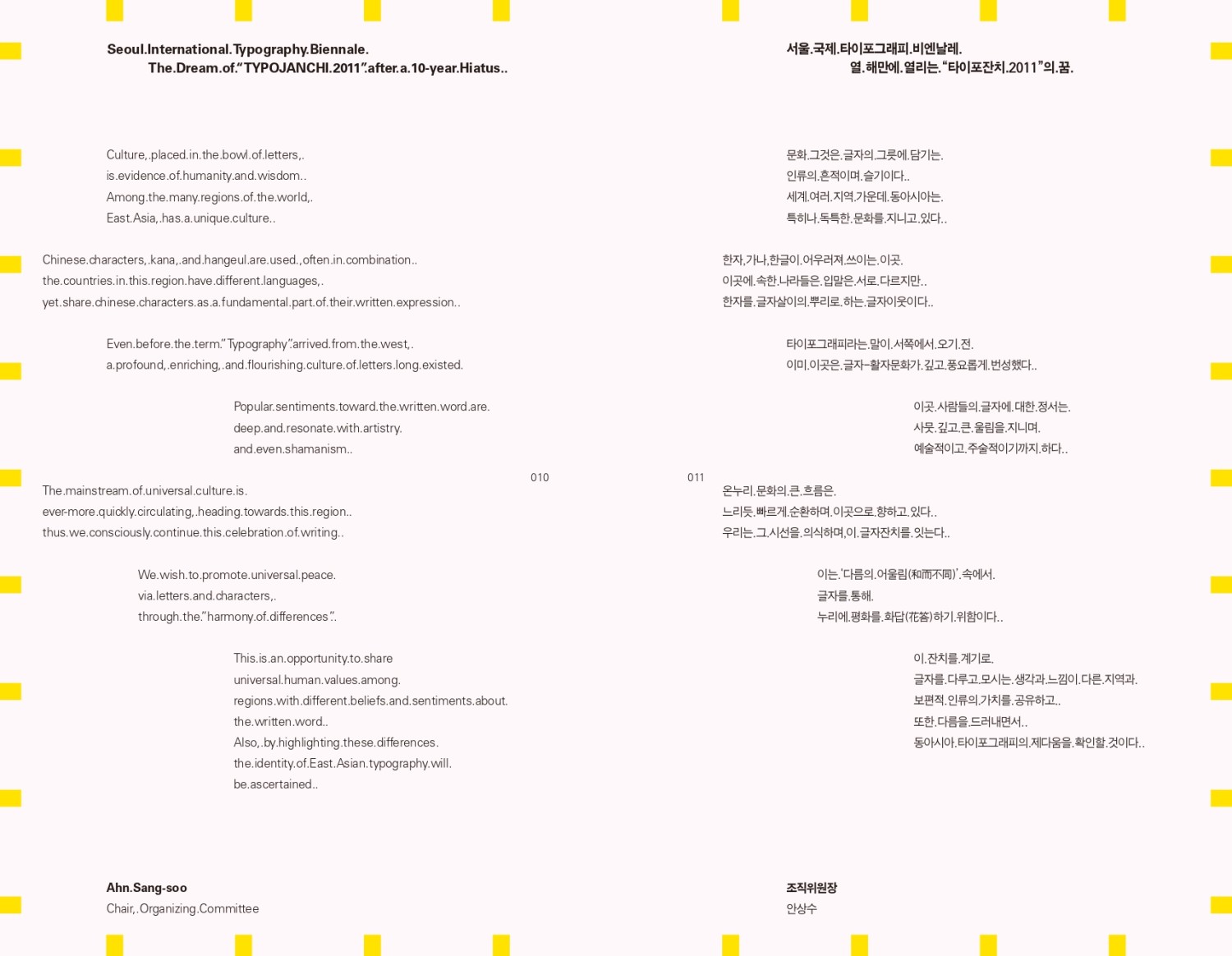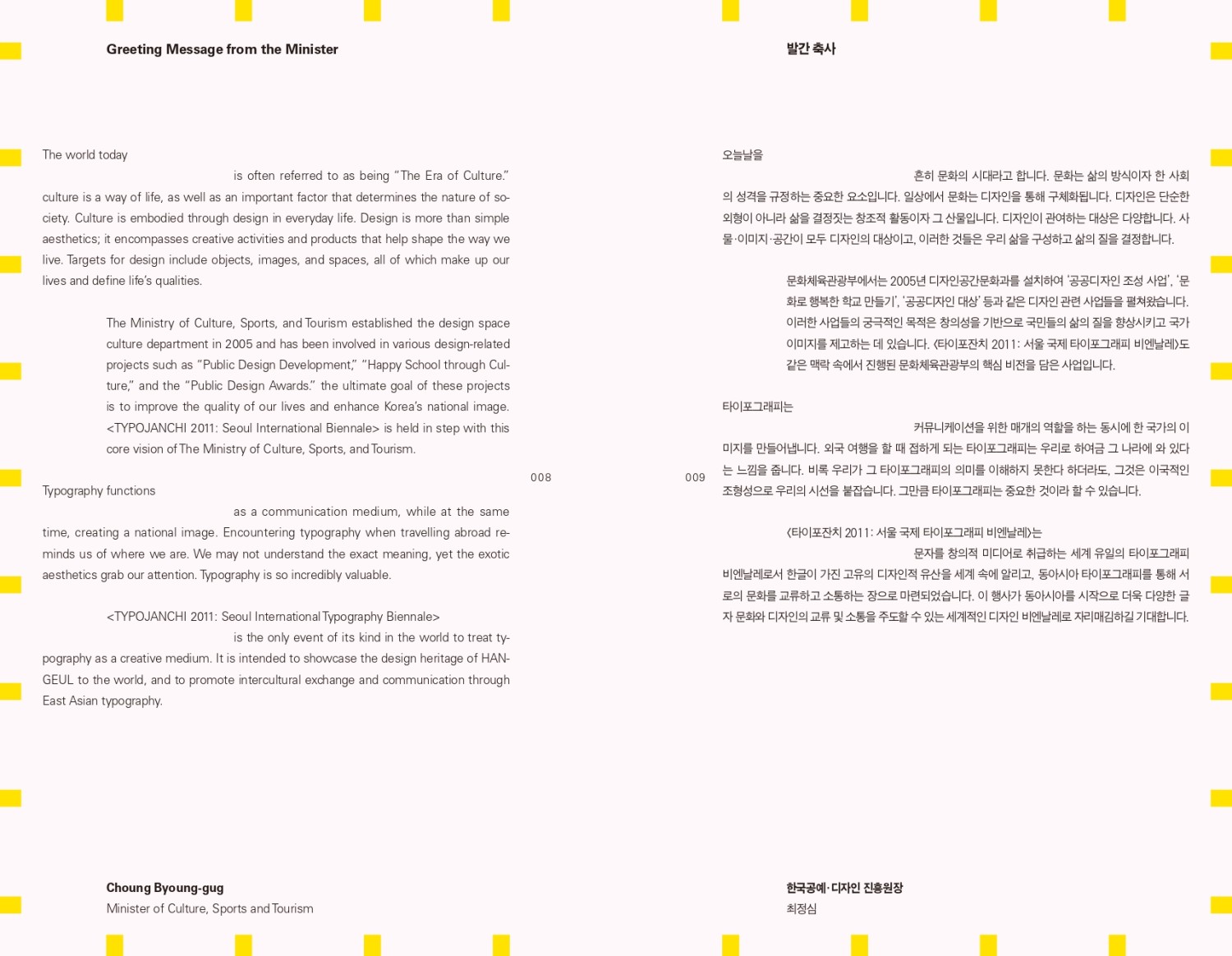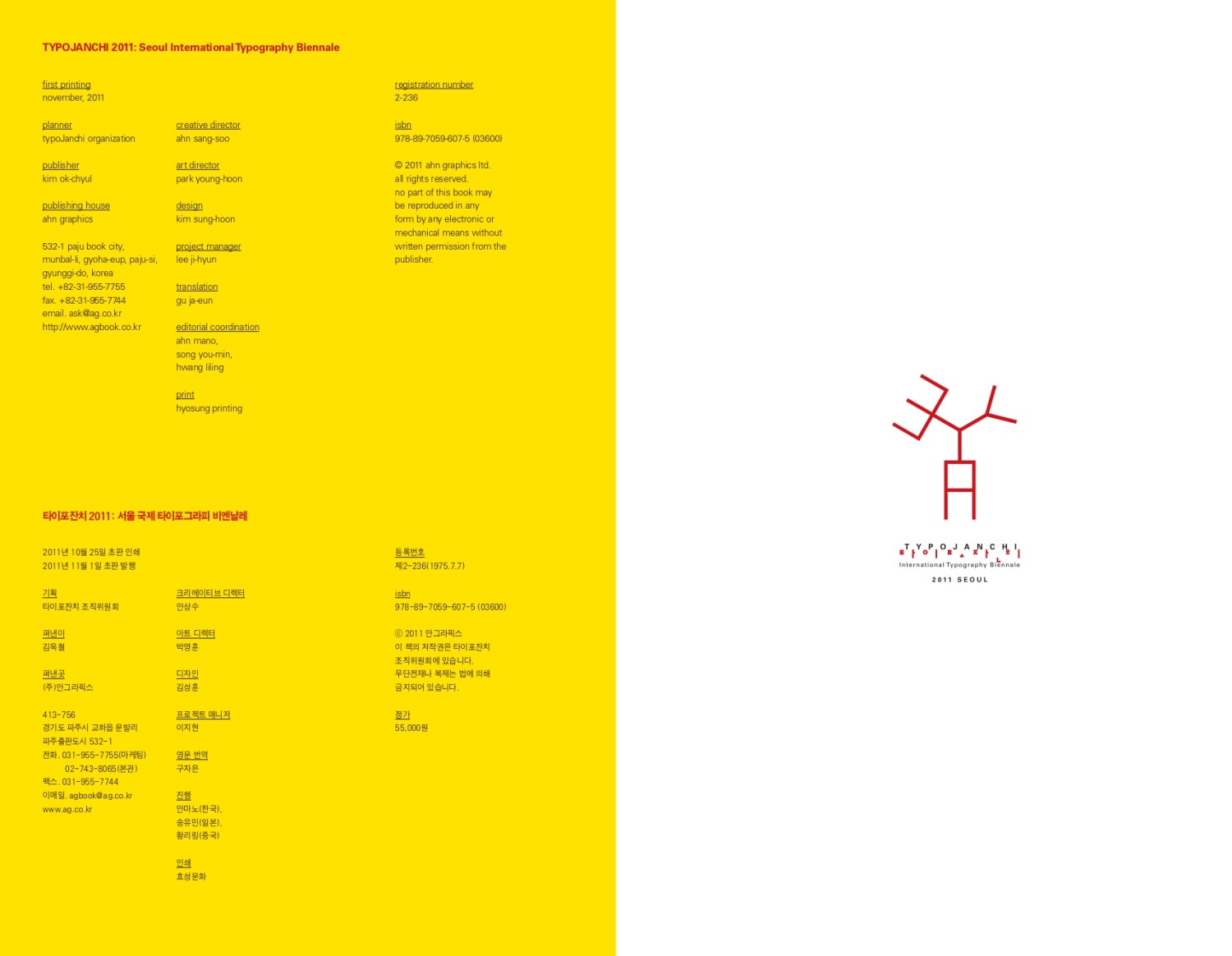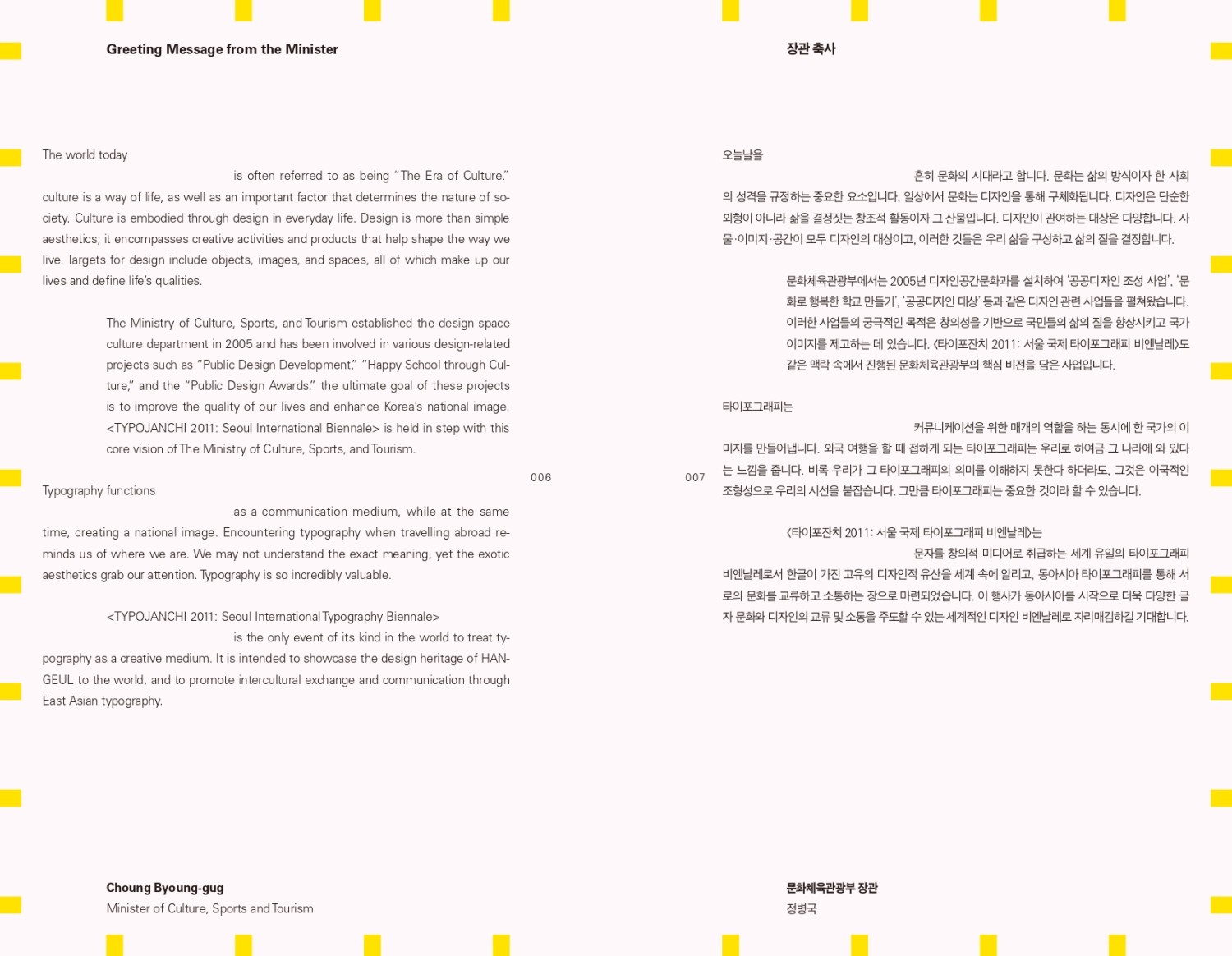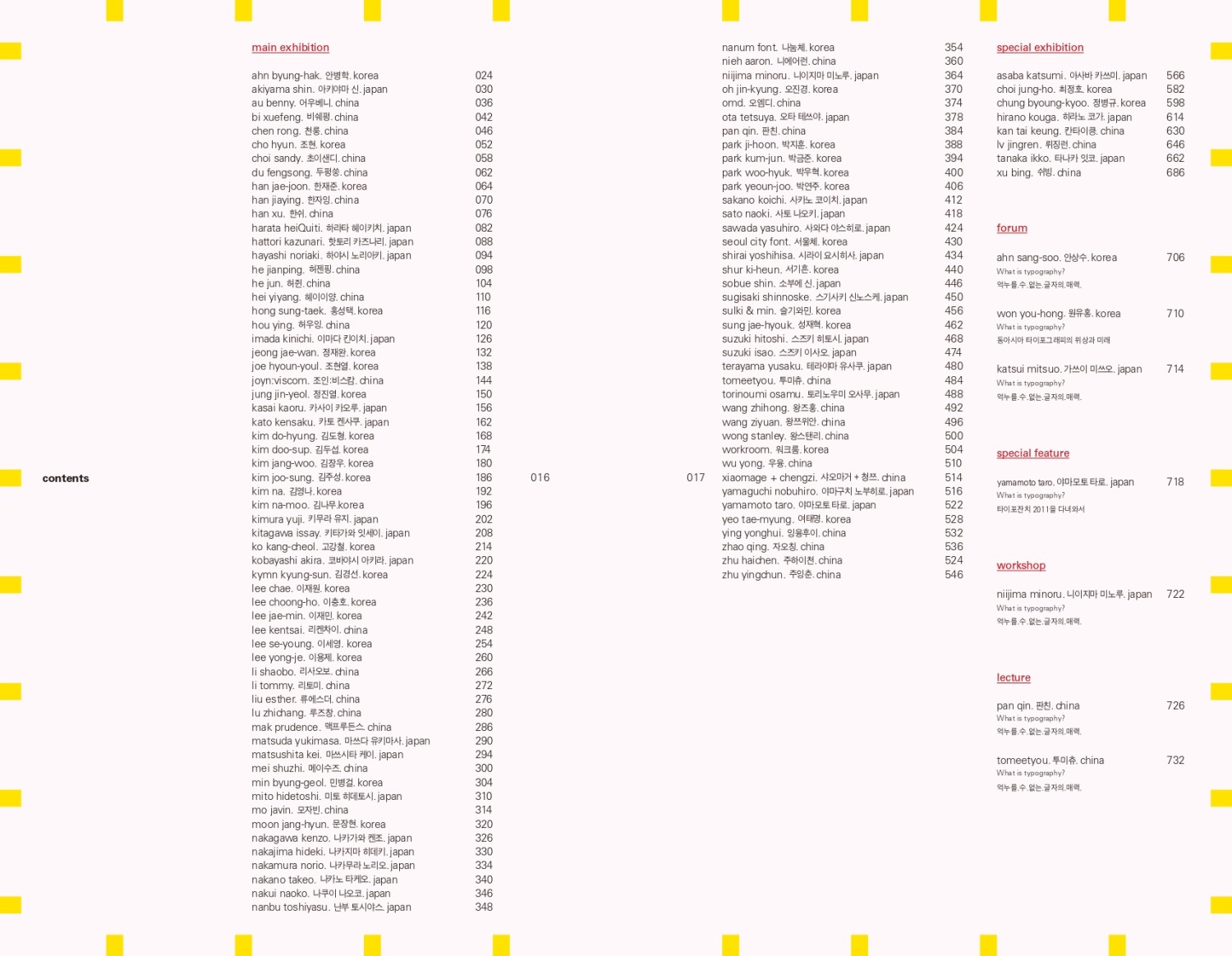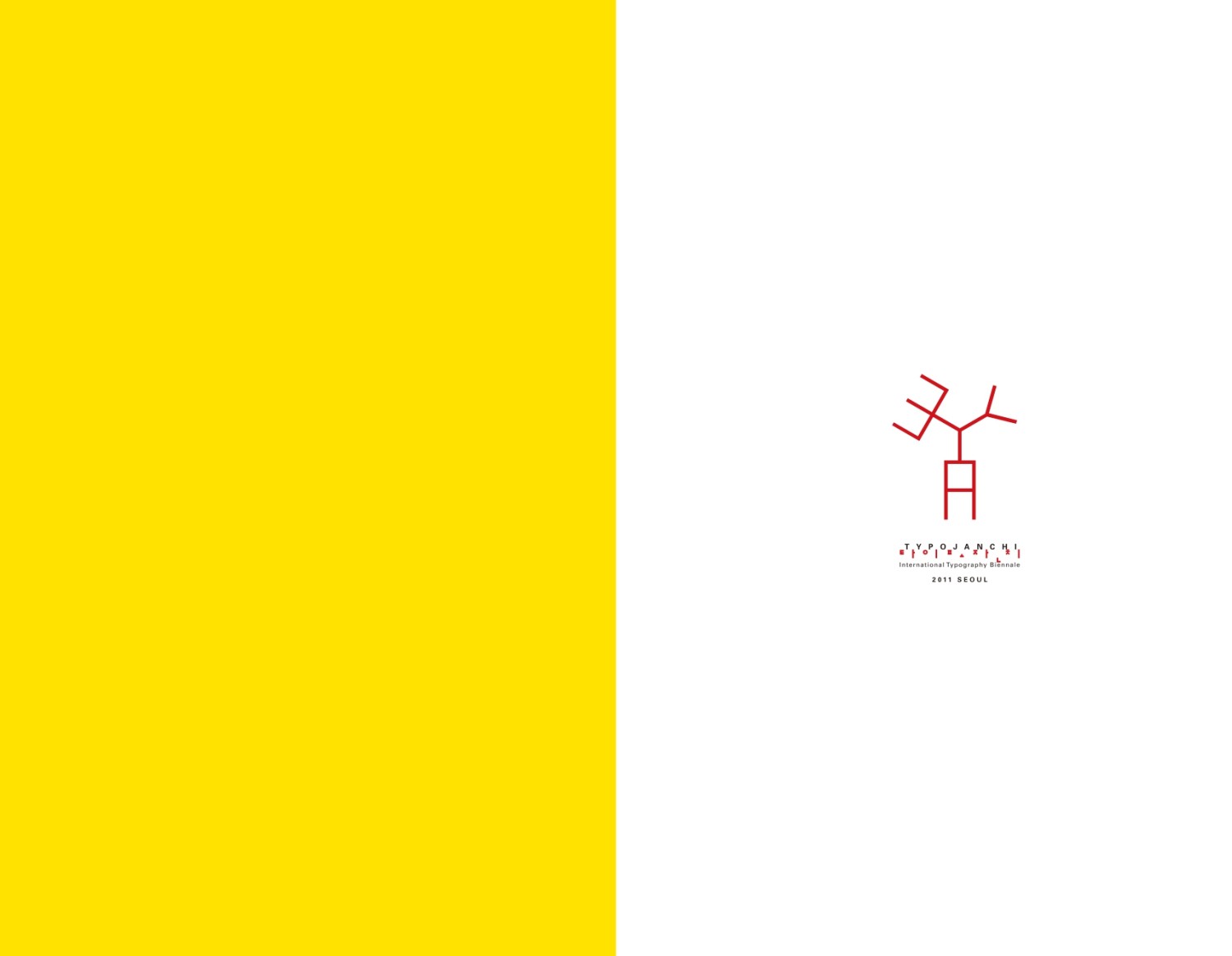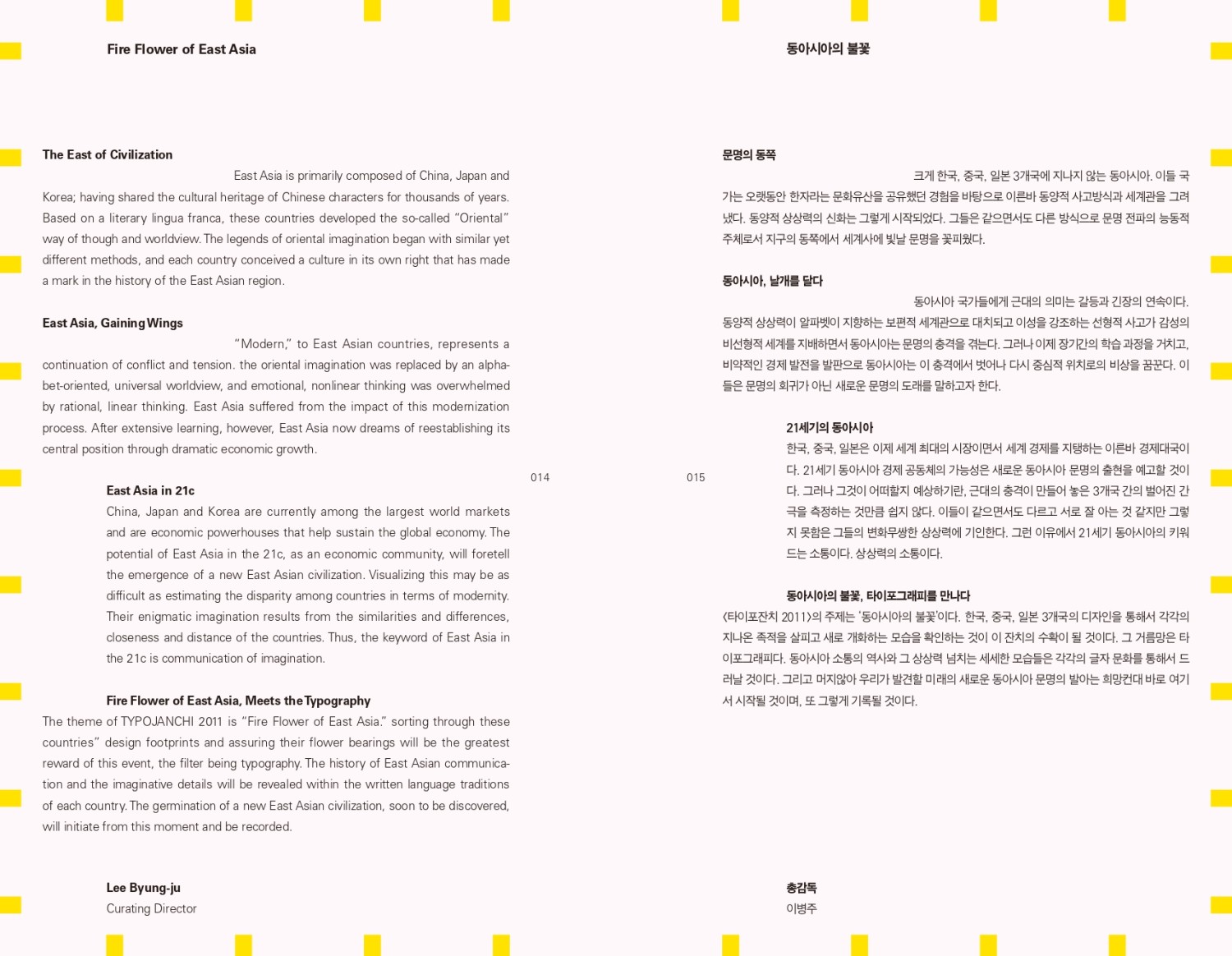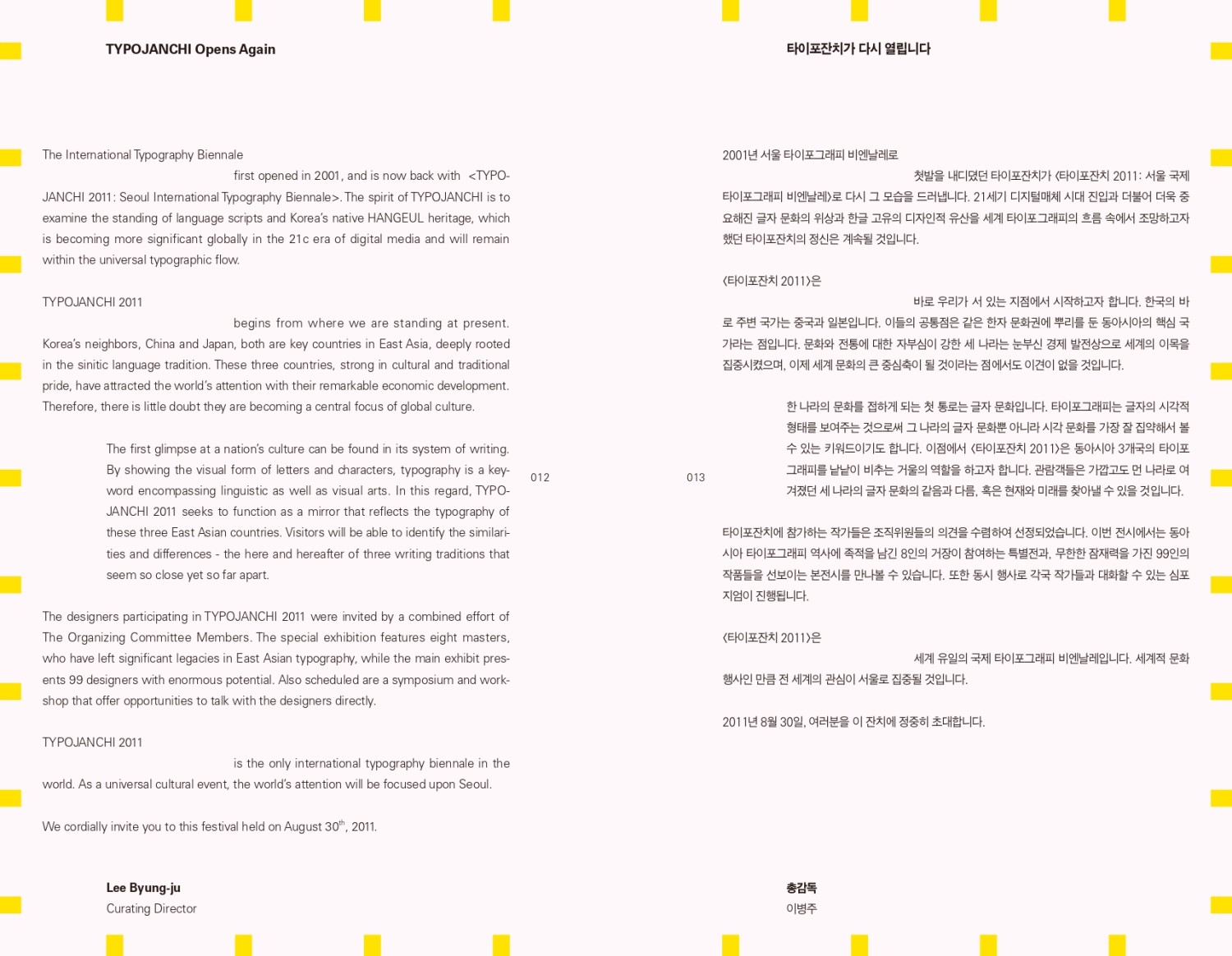
타이포잔치 2011: 동아시아의 불꽃
• 문자와 동아시아
• 예술의전당 서예박물관
• 2011년 8월 30일 – 2011년 9월 14일
10년의 공백을 넘어, 타이포잔치가 다시 불을 지폈다. 《동아시아의 불꽃》이라는 제목 아래 열린 2회 타이포잔치는, 한·중·일 99인의 디자이너가 참여한 동아시아 타이포그래피의 동시대적 감각과 전통의 흔적을 함께 보여주는 자리였다. 예술의전당 서예박물관에서 열린 이번 비엔날레는, 기자간담회, 본전시, 특별 전시, 포럼, 출판까지 다양한 구성으로 동아시아 문자 문화의 깊이를 입체적으로 풀어냈다. 전통 서예와 현대 타이포그래피가 같은 공간에서 공명하며, 활자가 단순한 정보 전달을 넘어 정체성과 감성, 시대정신을 품고 있다는 사실을 다시금 일깨웠다. 총감독 이병주의 기획 아래 타이포잔치는 다시금 한국 디자인계의 중심 무대로 돌아왔고, 문화체육관광부의 공식 지원을 받는 국제 디자인 비엔날레로 자리매김하게 되었다. 8,000여 명의 관람객이 찾은 이 전시는, 활자의 온기와 불꽃이 어떻게 다시 타오를 수 있는지를 보여준 상징적인 복귀였다.
총감독
이병주
참여 작가
• 고강철 (한국)
• 김경선 (한국)
• 김도형 (한국)
• 김두섭 (한국)
• 김영나 (한국)
• 김장우 (한국)
• 김주성 (한국)
• 나눔체 (한국)
• 나카가와 켄조 (일본)
• 나카노 타케오 (일본)
• 나카무라 노리오 (일본)
• 나카지마 히데키 (일본)
• 나쿠이 나오코 (일본)
• 난부 토시야스 (일본)
• 니에어런 (중국)
• 니이지마 미노루 (일본)
• 두펑쑹 (중국)
• 루즈창 (중국)
• 뤼징런 (중국)
• 류에스더 (중국)
• 리사오보 (중국)
• 리켄차이 (중국)
• 리토미 (중국)
• 마쓰다 유키마사 (일본)
• 마쓰시타 케이 (일본)
• 맥프루든스 (중국)
• 메이수즈 (중국)
• 모자빈 (중국)
• 문장현 (한국)
• 미토 히데토시 (일본)
• 민병걸 (한국)
• 박금준 (한국)
• 박연주 (한국)
• 박우혁 (한국)
• 박지훈 (한국)
• 비쉐펑 (중국)
• 사와다 야스히로 (일본)
• 사카노 코이치 (일본)
• 사토 나오키 (일본)
• 샤오마거 + 청쯔 (중국)
• 서기흔 (한국)
• 서울체 (한국)
• 성재혁 (한국)
• 소부에 신 (일본)
• 쉬빙 (중국)
• 스기사키 신노스케 (일본)
• 스즈키 이사오 (일본)
• 스즈키 히토시 (일본)
• 슬기와민 (한국)
• 시라이 요시히사 (일본)
• 아사바 카쓰미 (일본)
• 아키야마 신 (일본)
• 안병학 (한국)
• 야마구치 노부히로 (일본)
• 야마모토 타로 (일본)
• 어우베니 (중국)
• 여태명 (한국)
• 오엠디 (중국)
• 오진경 (한국)
• 오타 테쓰야 (일본)
• 왕스탠리 (중국)
• 왕즈훙 (중국)
• 왕쯔위안 (중국)
• 우융 (중국)
• 워크룸 (한국)
• 이마다 킨이치 (일본)
• 이세영 (한국)
• 이용제 (한국)
• 이재민 (한국)
• 이재원 (한국)
• 이충호 (한국)
• 잉융후이 (중국)
• 자오칭 (중국)
• 정병규 (한국)
• 정재완 (한국)
• 정진열 (한국)
• 조현 (한국)
• 조현열 (한국)
• 주잉춘 (중국)
• 주하이천 (중국)
• 천룽 (중국)
• 초이샌디 (중국)
• 최정호 (한국)
• 카사이 카오루 (일본)
• 카토 켄사쿠 (일본)
• 칸타이킁 (중국)
• 코바야시 아키라 (일본)
• 키무라 유지 (일본)
• 키타가와 잇세이 (일본)
• 타나카 잇코 (일본)
• 테라야마 유사쿠 (일본)
• 토리노우미 오사무 (일본)
• 투미츄 (중국)
• 판친 (중국)
• 하라타 헤이키치 (일본)
• 하야시 노리아키 (일본)
• 한쉬 (중국)
• 한자잉 (중국)
• 한재준 (한국)
• 핫토리 카즈나리 (일본)
• 허우잉 (중국)
• 허젠핑 (중국)
• 허쥔 (중국)
• 헤이이양 (중국)
• 홍성택 (한국)
• 히라노 코가 (일본)